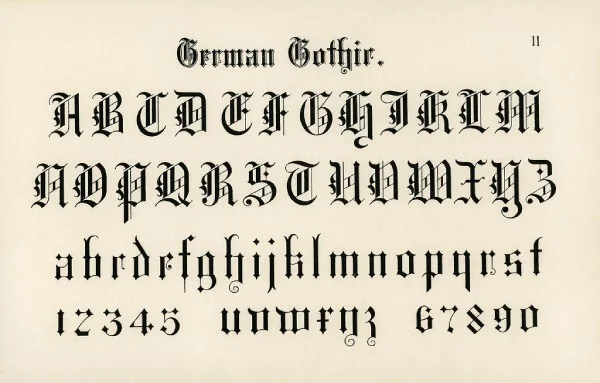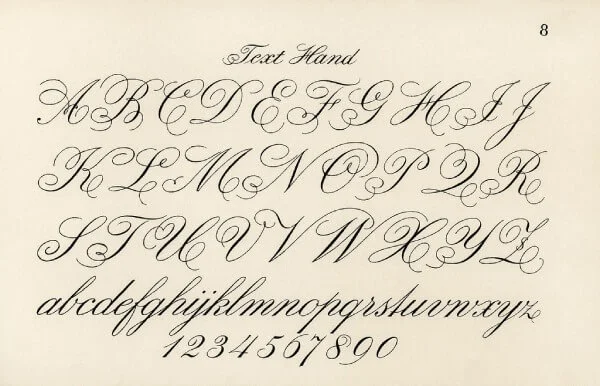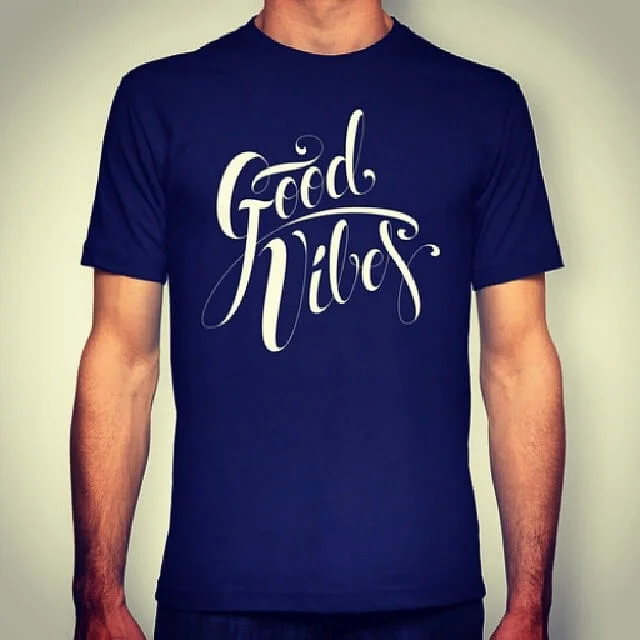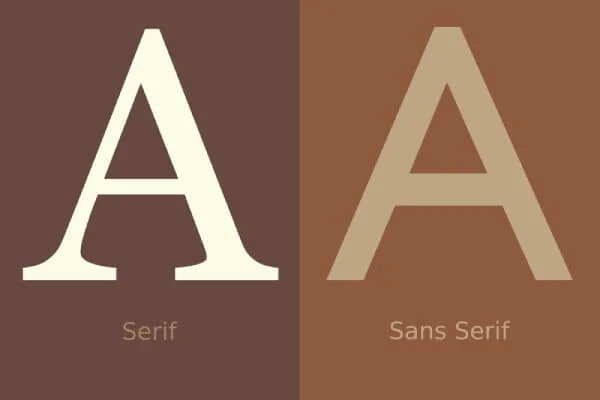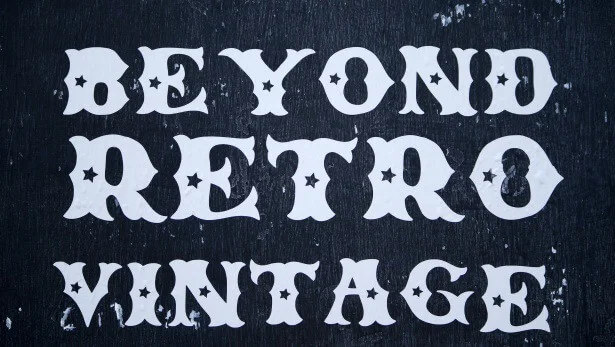
Stil und Schriftart für Ihre individuellen T-Shirts
Wenn Beschriftung die perfekte Lösung für Ihre individuellen T-Shirts ist.
Möchten Sie schöne und preiswerte T-Shirts individuell gestalten, vielleicht für eine Mottoveranstaltung ? Schriftzüge eignen sich hervorragend, um auffällige Kleidung zu kreieren. Sie fragen sich, was Schriftzüge sind? Dann schauen wir uns die Definition an und wie sie Ihnen helfen können, stylische T-Shirts zu gestalten.
Was ist Lettering und wie kann es Ihnen helfen?
Lettering lässt sich ins Italienische mit „Kalligrafie“ übersetzen. Genauer gesagt bezeichnet es die Kunst der Typografie und deren Verwendung zu rein dekorativen Zwecken . Es ist kein Zufall, dass diese Technik in der Werbung, in Comics und sogar in der Innenarchitektur weit verbreitet ist. Eine weitere Möglichkeit, Lettering einzusetzen, ist das Bedrucken von T-Shirts mit typografischen Zeichen, kombiniert mit einem bestimmten Design oder Bild. Kalligrafie auf T-Shirts ist eine tolle Möglichkeit, originelle, stylische und wirklich auffällige Stücke zu kreieren. Das Tragen solcher individueller T-Shirts verleiht Ihnen einen einzigartigen Stil, besonders wenn Sie kurze Aphorismen oder kurze Songzitate drucken lassen! Wenn Sie ein Unternehmen besitzen , können Sie sie zur Bewerbung von Veranstaltungen nutzen (lesen Sie hier mehr dazu: „ Individuelle T-Shirts für Events “). Die Teilnehmer werden die schönen T-Shirts auch nach der Veranstaltung gerne tragen! Um auf den Punkt zurückzukommen: Lettering bezeichnet im Allgemeinen die manuelle Erstellung neuer Zeichen, inspiriert von bestimmten Schriftarten.
In den nächsten Abschnitten werden wir uns die wichtigsten Schriftarten ansehen, mit denen Sie beginnen können, wenn Sie sich mit Schriftgestaltung beschäftigen möchten.
Schriftarten als Ausgangspunkt für Beschriftungen
Hier sind einige grundlegende Schriftarten, mit denen Sie das Schreiben üben und sich Inspiration für Ihren eigenen persönlichen Stil holen können (zum Bedrucken Ihrer T-Shirts!):
• Sans serif
• Serif
• Schreibschrift / Kursivschrift
• Jahrgang
• Gotisch – Frakturschrift
Schriftzug mit serifenloser Schriftart
Serifenlose Schriften sind ideal für Anfänger im Bereich Lettering. Dank ihrer einfachen Formen können Sie sich ganz auf die einzelnen Buchstaben und deren Beziehung zueinander konzentrieren. Ein besonderes Merkmal von serifenlosen Schriften macht sie perfekt für den individuellen T-Shirt-Druck: Sie sind unglaublich gut lesbar. Auch für kurze Sätze sind sie ideal! Mit serifenlosen Schriften können Sie im Handumdrehen tolle Letterings erstellen und Ihre T-Shirts zu echten Unikaten machen. Individuell gestaltete T-Shirts mit serifenlosen Schriftarten
Schriftgestaltung mit Serifenschriften
Serifenschriften ähneln den serifenlosen Schriften, zeichnen sich aber durch kleine, dekorative Striche an den Enden der Buchstaben aus. Diese Schriften eignen sich hervorragend, um die Beschriftung Ihrer individuellen T-Shirts eleganter und harmonischer zu gestalten. Sie sind auch eine tolle, originelle Geschenkidee! Lesen Sie den Artikel „ Individuelle Geburtstags-T-Shirts “, um mehr zu erfahren.
Schreibschrift
Schriftarten für individuelle T-Shirts Wie Sie wissen, ist die Schreibschrift ein Schreibstil, bei dem die Buchstaben fließend ineinander übergehen. Schreibschrift und Kalligrafie sind jedoch nicht dasselbe. Die Schreibschrift folgt einigen Regeln der Kalligrafie, insbesondere der Regel der aufsteigenden und absteigenden Strichstärke. Der Vorteil der Schreibschrift liegt darin, dass Sie nicht durch die Möglichkeiten Ihres Stiftes eingeschränkt sind! Mit einem Kalligrafie-Werkzeug wie einer Feder können Sie beispielsweise nur eine bestimmte Strichstärke erzeugen. Bei der Schreibschrift hingegen können Sie jede beliebige Form gestalten, solange Sie grundlegende Prinzipien wie Gleichmäßigkeit, Ausgewogenheit und Abstände beachten.
Vintage-Schriftzug (Retro) für Ihre preisgünstigen, individuell gestalteten T-Shirts
Retro-Vintage-Schriftart für individuelle T-Shirts Vintage-Schriftzüge sind an einigen charakteristischen Merkmalen eindeutig erkennbar. Hier sind einige davon:
• Dekorationen
• Serif
• Textur
• Farben
Im Internet finden Sie tausende Beispiele für Vintage-Schriftzüge – wir empfehlen Ihnen Pinterest als Inspirationsquelle. Vintage-Schriftzüge eignen sich hervorragend für den T-Shirt-Druck bei Vintage- oder traditionellen Veranstaltungen (oder sind auch perfekt für den Hipster-Stil!). Sie haben sich zudem zu einem großen Trend in der Designbranche entwickelt, da immer mehr Menschen die Schönheit des Vintage-Stils entdecken.
Gotische Schriftzüge für Ihre T-Shirts
Gotische Schriftzüge für individuelle T-Shirts Die gotische Schrift ist ein vom Mittelalter inspirierter kalligrafischer Stil: Sie eignet sich hervorragend für den Druck von T-Shirts im Gothic- oder Dark-Style. Diese Schriftart ist ideal für weiße Schrift auf schwarzem Grund; beispielsweise könnte man ein Zitat aus einem Metal-Song, vielleicht kombiniert mit einem schönen gotischen Design, verwenden. Kurz gesagt: Dieser Stil ist sehr markant und erzeugt eine ansprechendere Optik als andere, schlichtere Stile.
Abschließend